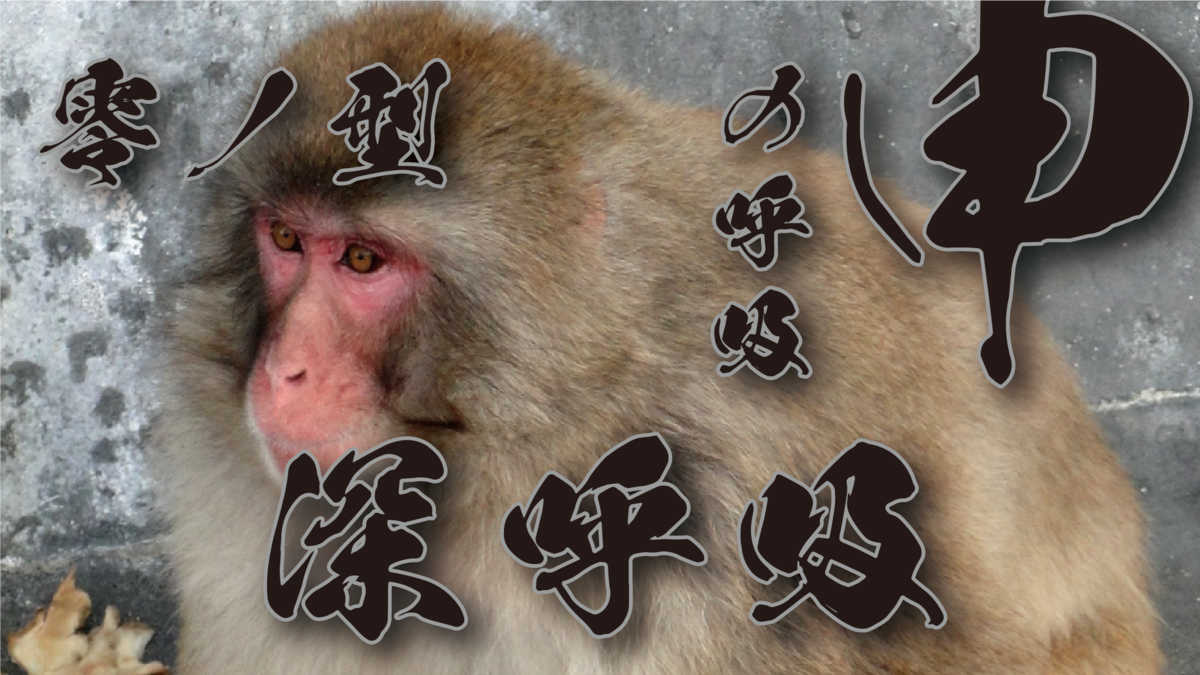
動画での使用にも適した、国民的アニメ「鬼滅の刃」でお馴染みの鬼滅フォント「黒龍爽/心龍爽」
国民的アニメ「鬼滅の刃」の使用でお馴染みの昭和書体の鬼滅フォントとなる荒々しい筆書体「黒龍爽」と穏やかな筆書体「心龍爽」。
それぞれ、従来の書体からカスレを少なくし容量を抑え、カッティングや動画にも使いやすくなっている書体として「黒龍爽」「心龍爽」としてAdobe Fontsに収録された。
荒々しい“筆の呼吸”を感じる筆書系デザイン書体「黒龍爽」
「黒龍」は、牡の龍が暗雲立ち込める空を荒々しく漂うさまをイメージして作られた筆書系デザイン書体。
太い線と細い線が入り混じる緩急のついた画線は、まるで猛々しい龍の感情の抑揚を表わしているかのようです。正方形を意識しすぎることなく、ダイナミックに描かれた一つ一つの文字は、一見、アンバランスにも見えるが、文章として組むとその力強いイメージで見事に調和。
「黒龍爽」では、従来の書体である「黒龍」のカスレを少なくし容量を抑え、カッティングや動画にも使いやすくなっている書体となる。
穏やかな“筆の呼吸”を感じる筆書系デザイン書体「心龍爽」
「心龍」は、穏やかな牝の龍が天空から語りかけるイメージで作られた筆書系デザイン書体。
細い画線で、文章に使用すると厳かでありながら、優しいイメージを持たせる事が可能。
「心龍爽」では、従来の書体である「心龍」のカスレを少なくし容量を抑え、カッティングや動画にも使いやすくなっている。